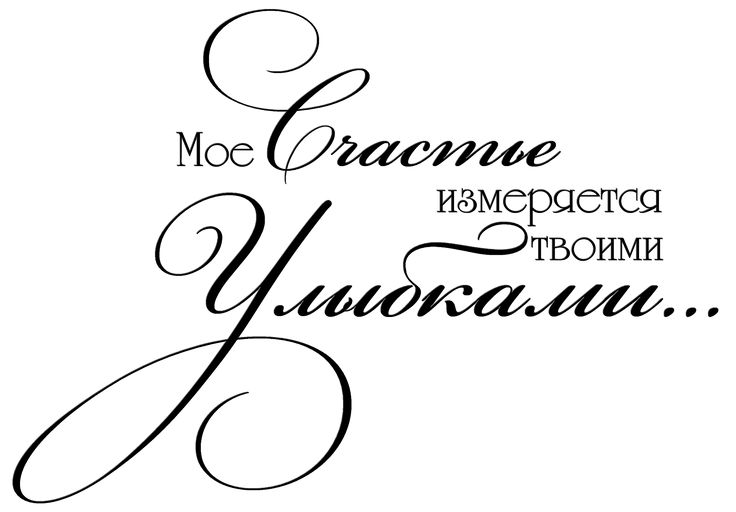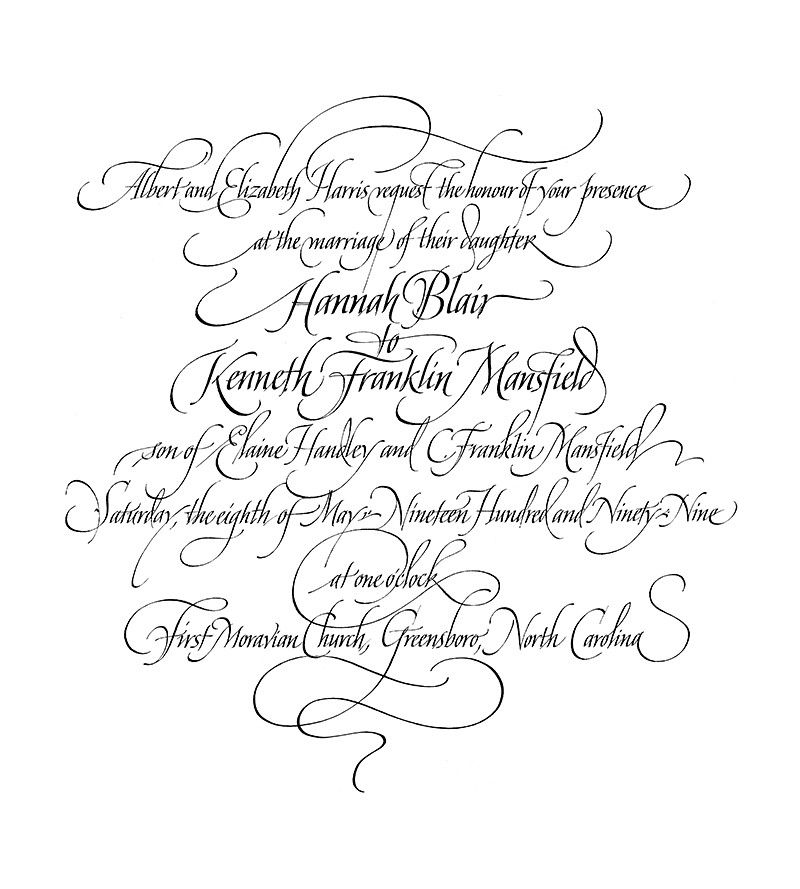
Шрифт для открытки: 10 кириллических шрифтов, чтобы подписывать открытки и подарки – DIY и мастер-классы
Красивый шрифт для открытки — 73 фото
20+ лучших шрифтов для открыток для живописного дизайна
Несмотря на то, что существует множество шрифтов, когда дело доходит до дизайна, шрифты для открыток черпают вдохновение из старинных произведений искусства, причудливых дисплеев, классного стиля и многого другого, чтобы сделать ваши проекты выделяющимися.